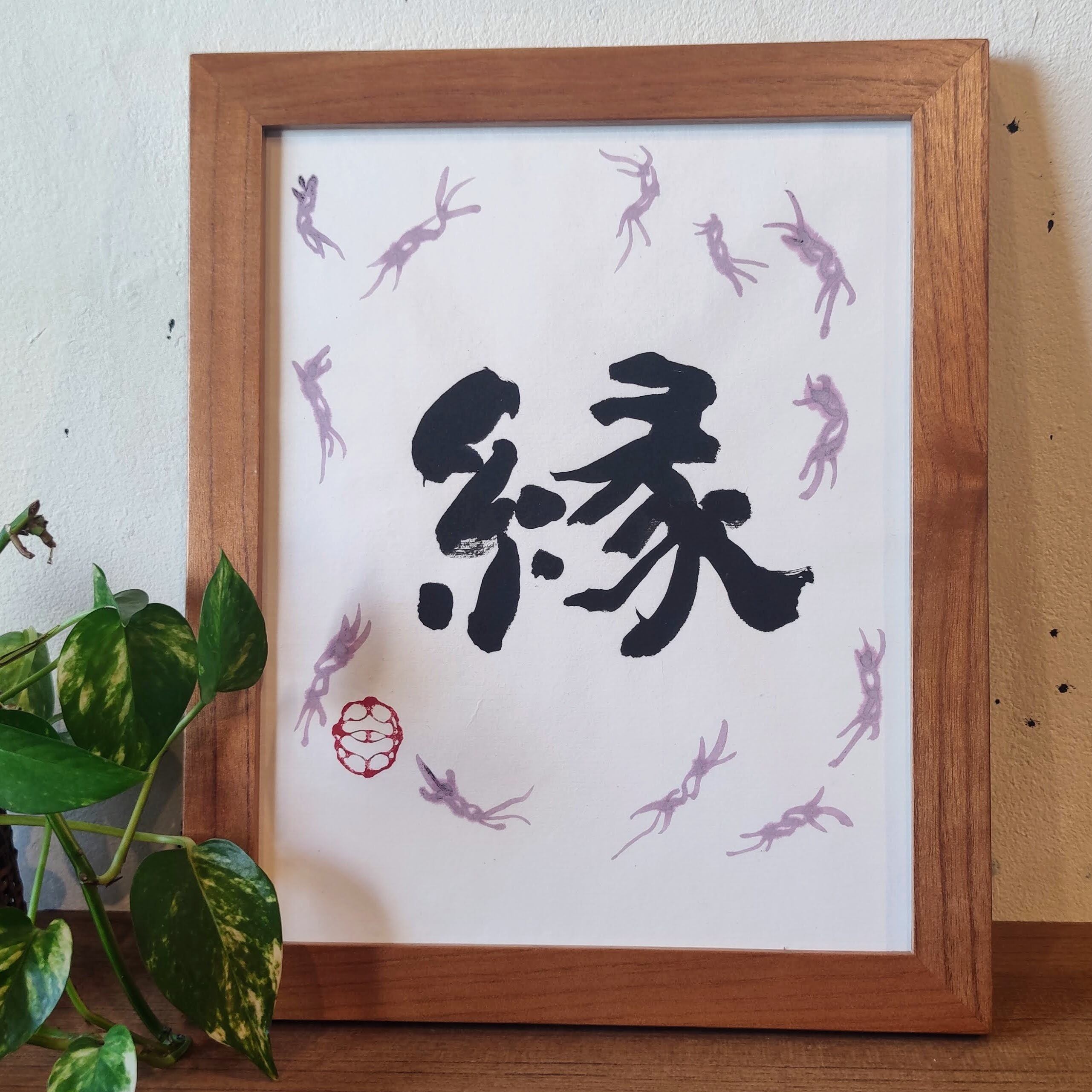
☀愛の糸♡命名書☀中サイズ
書どう家胡桃が手掛ける
書作品としての命名書
文字から
お名前への想いやその子の雰囲気を
感じられるように
大きくなって自分の名前が好きになれるように
その子だけの作品を制作いたします。
名前の周りを舞い囲む「糸」の文字(サンプルではピンク)は色を選択できます。
※「糸」の文字の配置はその作品によって異なります。
いかにもな命名書でなく飽きずに飾れる♡
インテリアに馴染む作品をご提供いたします。
広がりつながる愛の糸に囲まれた
☀愛の糸♡命名書☀
お名前は甲骨文字「糸」に囲まれます。
書どう家 胡桃がモチーフにする、甲骨文字「糸」は人が踊るような不思議な形。
この文字につながれという想いを込めて《DNA、へその緒、植物、愛、生命力…》を表現しています。
誕生を皆で喜んだ瞬間の
愛に満ちた想いを作品にして
新鮮なまま凝結させます♡
眺めることで初心を思い出し
また未来へと想いを乗せて進む
赤ちゃん、ぱぱまま家族を囲み
広がりつながる愛の糸♡
新たないのちの誕生
幸せのおすそわけをいただき
愛に満たされながら
希望や喜びを祈り
書かせていただく命名書は
私が願い表現する
「愛の糸」に満たされた世界への
祈りを込めたサクヒン♡
書には魂が宿ります。お客様のお気持ちと、作り手の想いがうまく重なれば、「合作」となって贈られた方や観る人の心に響きます。